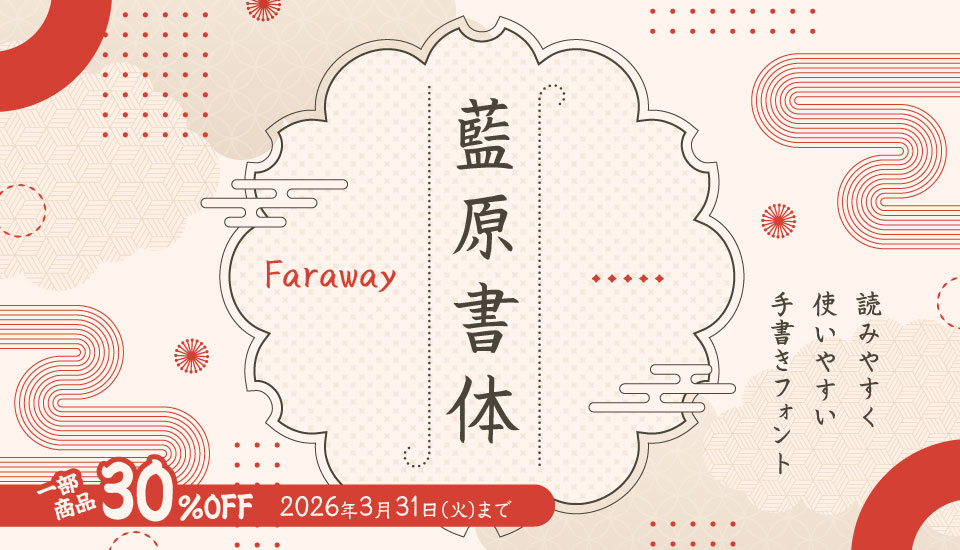
藍原書体/Faraway 藍原彼方による手書き書体ブランド
藍原彼方による手書き書体ブランド「藍原書体/Faraway」
ゲーム制作者としても活動する藍原彼方氏によるブランド「Faraway」が提供する『藍原筆文字楷書』を代表とした『藍原書体』は、読みやすく使いやすい手書きフォントです。
「藍原書体/Faraway」について
『やりたいことはとりあえずやってみる』が座右の銘。長年習った書道、自身の書を元にフォントを作ってみたいと思った作者である藍原彼方氏は、ゲーム制作者としても活動しており、自身のサイトでゲームと合わせてフォントを公開しようと思い制作を始めました。
フォントなどの素材は他者に使ってもらってこそ意味があるので、読みやすく使いやすいフォントを目指して制作しています。
藍原江戸文字・藍原勘亭流
藍原筆文字隷書・藍原筆文字楷書
1. 藍原筆文字楷書
2. 藍原サインペン
3. 藍原江戸文字
4. 藍原勘亭流
5. 藍原筆文字隷書
1. 藍原筆文字楷書
藍原書体/Faraway
藍原筆文字楷書
和の雰囲気を出したいときに。『藍原筆文字楷書』は書道歴20年以上の藍原彼方が作成した細めの楷書体フォントです。2015年にフリーフォント版を公開以来、季節の手紙や名刺、同人誌など個人での利用や、動画のテロップ、チラシ、冊子、ポスター作成などの商用利用、変わったところでは包丁の刻印や、キャラクターの書き文字にも採用されています。
2. 藍原サインペン
藍原書体/Faraway
藍原サインペン
読みやすい手書き文字が欲しいときに♪『藍原サインペン』は藍原彼方が手書きした文字を元に作成した細めのフォントになります。丁寧で読みやすい手書きフォントのため、季節の手紙や同人誌などの個人利用、動画テロップ、チラシ、冊子作成などの商用でのデザイン利用など用途は無限大ですので、あなたのデザインワークにご活用いただければ幸いです。
3. 藍原江戸文字
藍原書体/Faraway
藍原江戸文字
江戸っぽさ、日本っぽさを出したいとき、力強さが欲しいときなどにお勧めのフォントです。千社札などに使われる千社文字を参考に作成しています。勘亭流フォントよりも癖がないので比較的読みやすく、動画のサムネイルやバナー、目を引きたい広告などに向いています。
4. 藍原勘亭流
藍原書体/Faraway
藍原勘亭流
江戸っぽさ、日本っぽさを出したいとき、インパクトが欲しいときなどにおすすめ!『藍原勘亭流』フォントは藍原彼方が手書きした文字を元に作成したフォントです。『勘亭流』の言葉は知らなくても、歌舞伎の看板などで目にしたことがある方も多い書体だと思います。インパクトのあるフォントのため、チラシやポスター、バナーなどの広告デザインや動画のテロップやサムネイルなどにおすすめです!
5. 藍原筆文字隷書
藍原書体/Faraway
藍原筆文字隷書
和風や中華風のデザインにぴったりの古風なフォント『藍原筆文字隷書』は書道歴20年以上の藍原彼方が手書きした文字を元に作成したフォントです。『隷書』というと聞きなれないかもしれませんが、日本の紙幣や書籍の題字などにも使われていたり、意外と身近で目にしている書体です。実際の隷書体は癖が強く現代の漢字と字形がかなり異なる文字もあるため、一部の文字は読みやすいように現代の楷書に近い形にアレンジしています。